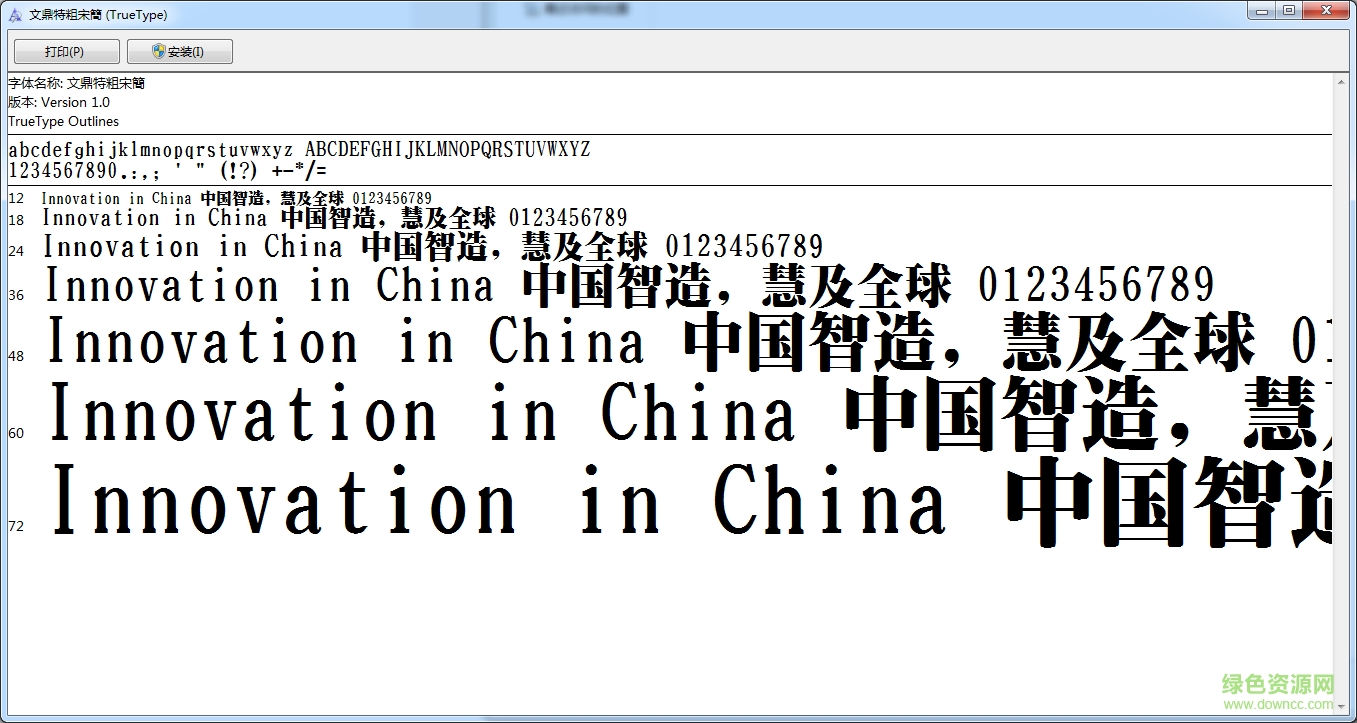
sungtieg ultra gb
sungtieg ultra gb是什么字体?sungtieg ultra gb 字体就是文鼎特粗宋简的英文简写,这款字体结合了黑体和宋体的共同特点,笔画粗壮,横细竖粗,形体干练,阅读性强!
sungtiegultragb字体介绍
sungtieg ultra gb是一款专门用于大字报方面的字体,比如报纸或杂志的头条都可以使用到这款字体。